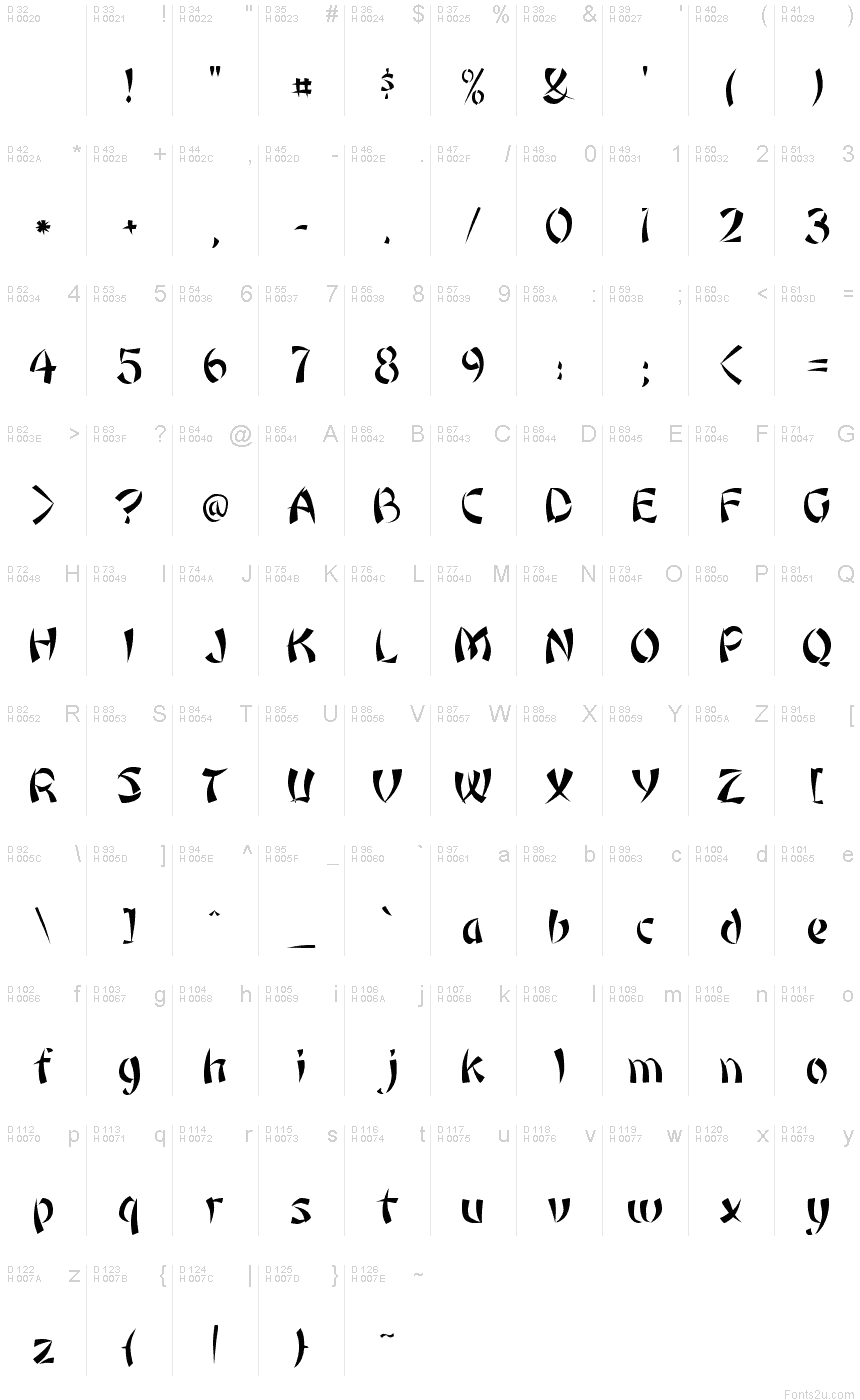
Orient1  Normal
Orient1 od Computer Support Corporation to bezpłatny font typu display o ostrych, kaligraficznych cięciach, zakrzywionych pociągnięciach i spiczastych detalach szeryfowych, które nadają literom rzeźbiony, niemal średniowieczny rytm. Formy łączą zaokrąglone krzywizny wewnętrzne z twardymi, kanciastymi zakończeniami, dzięki czemu krój jest dekoracyjny, nie stając się przy tym zbyt ozdobnym.
Orient1 świetnie sprawdza się w tytułach na plakatach, oprawie graficznej albumów, okładkach książek, logotypach i zaproszeniach, gdzie ta stylizowana, dawna energia może dopełnić projekt. Ten darmowy font pasuje również do podpisów, brandingu eventów i krótkich, ozdobnych nagłówków, ponieważ jego wyraziste kształty nadają charakteru krótkim tekstom bez konieczności stosowania dodatkowych upiększeń.